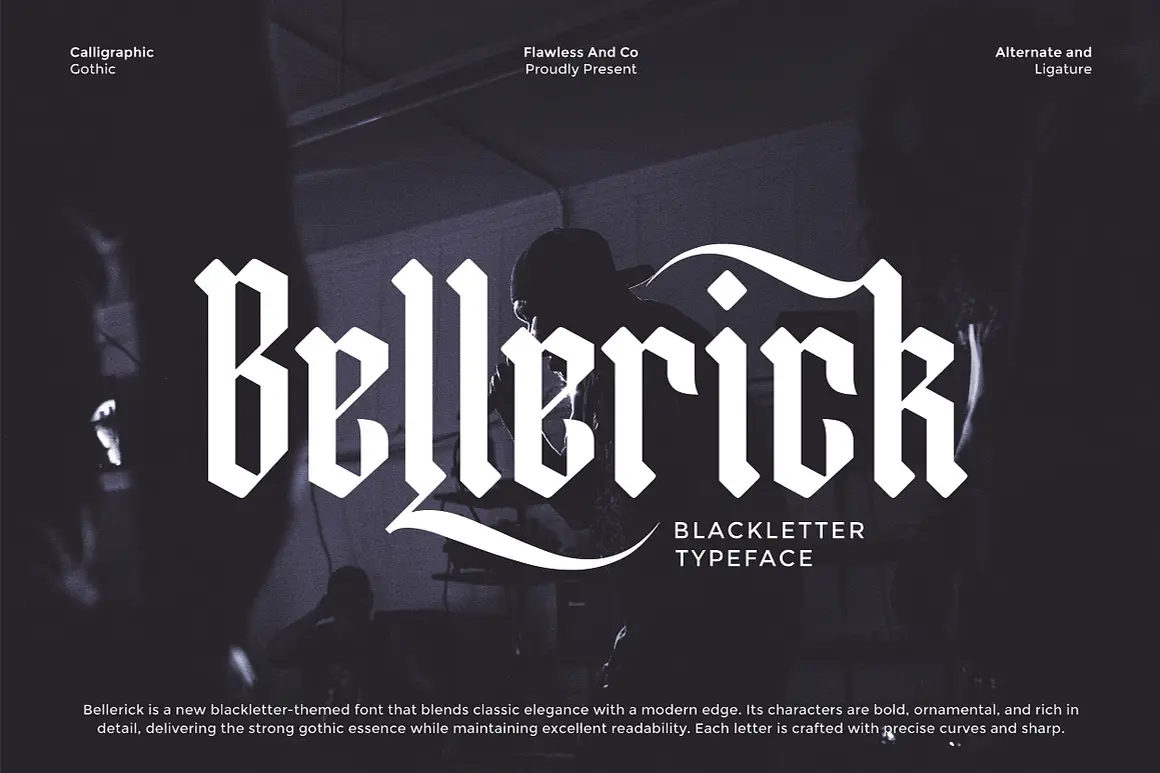
فونت بلک لتر مدرن و چشم گیر Bellerick
Bellerick یک فونت بلک لتر جسور و تزئینی است که زیبایی سنتی تایپوگرافی گوتیک را با ظرافتهای مدرن ترکیب میکند. طراحی این فونت با لبههای تیز و منحنیهای نرم، جلوهای قدرتمند و متمایز به هر پروژه میبخشد. اگر به دنبال تایپوگرافیای هستی که هم اصالت داشته باشه و هم خوانایی بالا، Bellerick انتخابی عالیه.
✨ ویژگیهای کلیدی
- 🔠 حروف بزرگ و کوچک با طراحی منحصربهفرد
- 🔤 شامل جایگزینها (Alternates) و لیگاتورها (Ligatures) برای ترکیبهای خاص
- 🔢 پشتیبانی از اعداد و علائم نگارشی استاندارد
- 🌍 پشتیبانی کامل از کاراکترهای چندزبانه برای استفاده بینالمللی
🎯 مناسب برای استفاده در
- طراحی لوگوهای خاص و برندهای قدرتمند
- استودیوهای تتو، گروههای موسیقی و هنرمندان مستقل
- پوسترهای تبلیغاتی، کاور آلبوم و طراحی مرچندایز
- بستهبندی محصولات با هویت جسور و تاریک
- طراحی لباس، برندهای خیابانی و فشن
- صفحات مجله، کتاب، و گرافیک شبکههای اجتماعی با جلوه دراماتیک
💡 چرا Bellerick انتخابی عالی برای طراحی برند و لوگو است؟
فونت Bellerick با ساختار قوی و جزئیات گوتیک، حس اعتماد، قدرت و اصالت را منتقل میکند. این فونت برای طراحانی ساخته شده که میخواهند هویت بصری ماندگار و متفاوت خلق کنند — از لوگوهای حرفهای گرفته تا تیترهای چشمگیر و بستهبندیهای خاص.